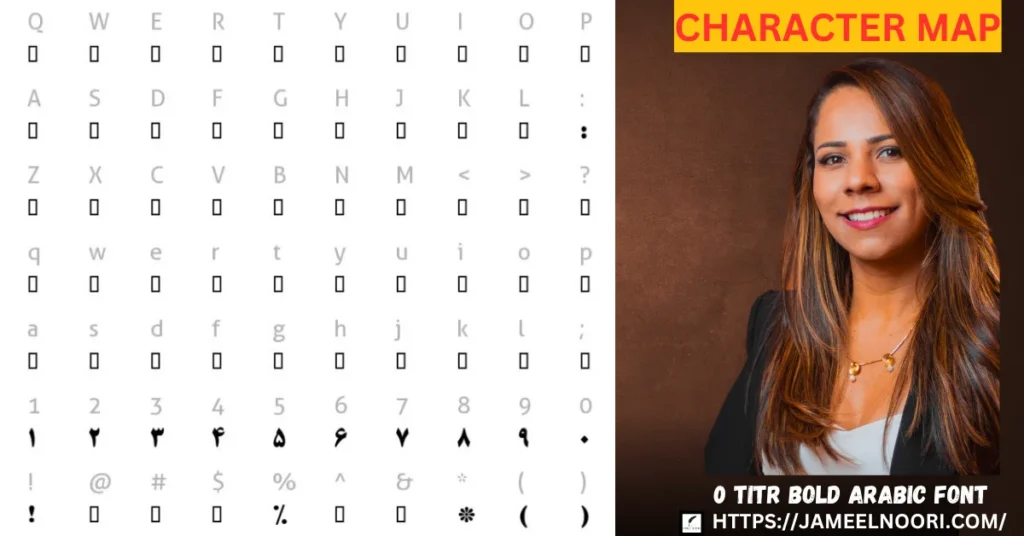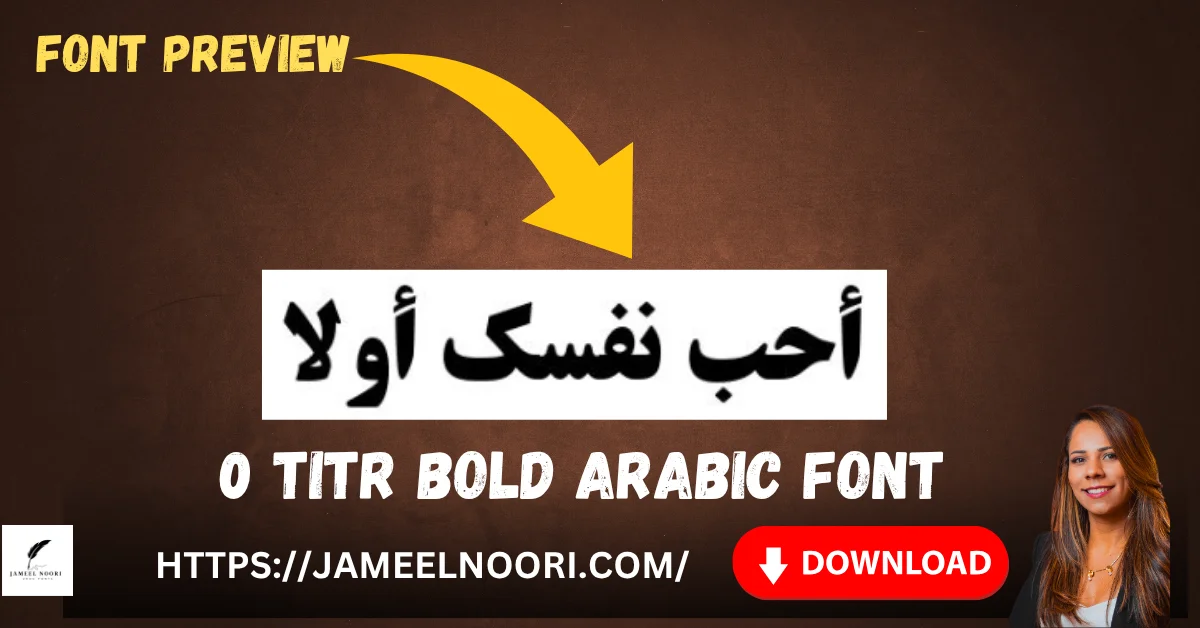
0 Titr Bold Arabic Font aik bohot hi mashhoor aur widely used Arabic font hai jo magazines, blogs aur digital headings me use hota hai. Yeh font apni bold TrueType styling ki wajah se bohot attractive lagta hai. Is font ka download count already 1,601,782 tak pohanch chuka hai aur 265 users ne isay 4.83/5 ki high rating di hui hai. Yeh stats prove karte hain ke Pakistan, Lahore aur Karachi ke users me bhi yeh font bohot demand me hai.
0 Titr Bold Arabic Font Features – Latest & Expert Choice
Is font ki kuch khaas features isay “best Arabic font” categories me laati hain.
✔ Key Features:
- Bold TrueType design jo headings ko bohot powerful banata hai.
- Magazines aur bloggers ka expert choice for headlines.
- Limited character map jo is font ko unique aur classy look deta hai.
- Perso-Arabic regions, specially Pakistan me trending.
- Urdu Fonts & Arabic Fonts collection me top-ranked.
0 Titr Bold Arabic Font Character Map Details
| Feature | Details |
| Font Name | 0 Titr Bold |
| Font Type | Bold TrueType |
| Best For | Headings, Magazines, Blogs |
| Regions | Pakistan, Iran, Arab Countries |
Character Map ko dekh kar aap notice karenge ke is font me characters ka range limited hai, jo design ko bohot unique banata hai. Bloggers aur graphic designers ke liye yeh quality bohot attractive hoti hai.
Why 0 Titr Bold Arabic Font is Best for Headings in Pakistan?
Pakistan me agar aap headings ko bold, clean aur focus-grabbing banana chahte hain to yeh font best option hota hai. Roman Urdu headings, Islamic texts, magazines aur blogs me yeh bohot classy feel deta hai. Yahan ke digital creators Arabic font download karte waqt specially is font ko prefer karte hain kyun ke yeh readability aur aesthetics dono maintain karta hai.
📌 Reasons for Popularity in Pakistan:
- Online magazines me sabse zyada used font.
- Bold styling se reader ka focus barhta hai.
- Urdu Fonts category me high-CTR performance.
- Easy compatibility with almost all devices.
Best Uses of 0 Titr Bold Font
Agar aap blogging, designing ya publishing me kaam karte hain to yeh font aapke liye perfect choice hai. Neeche kuch top use-cases diye gaye hain:
⭐ Best Use-Cases:
- Magazine Headlines
- Islamic Designs
- Web Banners
- Blog Post Headings
- Book Title Pages
- Social Media Posters
- Advertisement Artwork
Is font ke bold strokes aur clear character shapes isay har style me standout banate hain.
Comparison Table – 0 Titr Bold vs Other Best Arabic Fonts
| Feature | 0 Titr Bold | Regular Arabic Fonts |
| Weight | Extra Bold | Normal / Medium |
| Visibility | High | Medium |
| Style | Limited Characters | Wide Character Map |
| Best For | Headings | Paragraphs |
Ye comparison clearly show karta hai ke heading work ke liye yeh font unbeatable hai.
Agar aap Pakistan me apne blog, magazine ya digital designs ke liye koi best Arabic font dhoondh rahe hain to yeh font perfect option hai. Iski bold styling, high rating aur massive downloads isay top choice banate hain. Design projects me readability aur impact chahye to yeh font aapko impressive results dega.
What is 0 Titr Bold Arabic Font?
It is a bold TrueType Arabic font mainly used for headings and magazine titles.
Is this font free to download?
Yes, most platforms offer this font for free.
Can I use this font in Photoshop?
Yes, it is fully compatible with Adobe Photoshop.
Is it good for Urdu headings?
Yes, it works perfectly for Urdu, Roman Urdu, and Arabic-style headings.
Does it support InPage?
Yes, you can use it after installation.
Is it suitable for logo design?
Yes, its bold style is ideal for logos and branding.
Is it recommended for long paragraphs?
No, it is mainly for headings, not body text.
Does it include a complete character map?
It has a limited character map which makes it unique.
Is this font popular in Pakistan?
Yes, bloggers and designers in Pakistan widely use it.